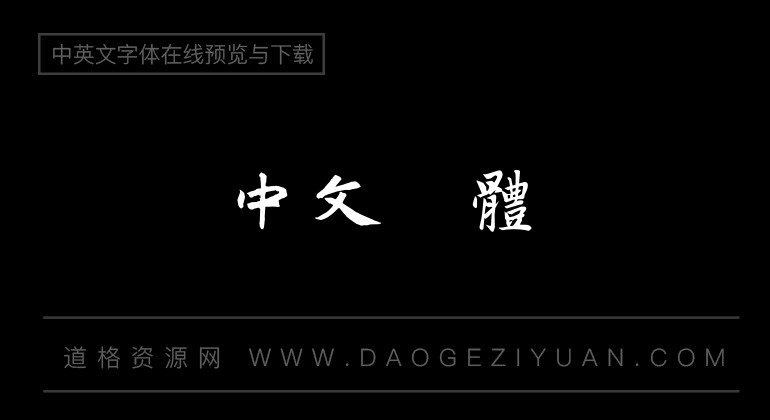
迷你繁赵楷
迷你繁赵楷字体是一种繁体中文字体,由台湾字体设计师柯元辉设计,是一种比较细小的字体,其字形精美,线条流畅,字体设计精致,比较符合中国传统繁体书法的风格,比较适合用于文字艺术、小型书籍和海报等设计上。
迷你繁赵楷是一款非常不错的手写艺术字体,具有很好的视觉感,适合于文化类的宣传设计、商业类品牌的广告和产品包装设计以及个性化文字排版等较多场景。